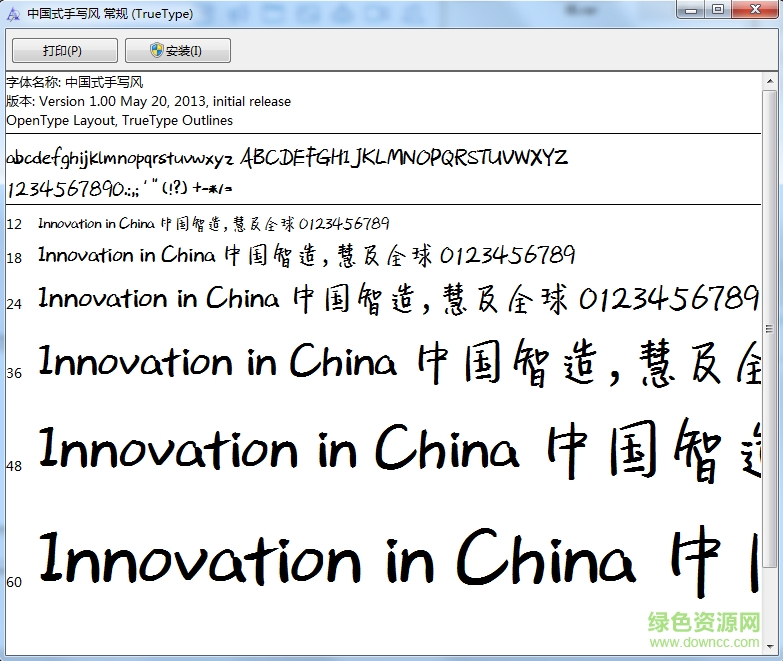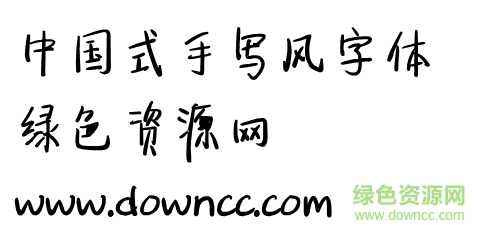
中國式手寫風(fēng)字體是一款很簡單常用的手寫字體,落筆干凈爽快、字跡工整簡約,喜歡的朋友快來綠色資源網(wǎng)下載吧!
中國式手寫風(fēng)字體有著獨特魅力的藝術(shù)字體,適用于美工創(chuàng)作、網(wǎng)站設(shè)計、平面設(shè)計、封面設(shè)計、名片設(shè)計等方面。